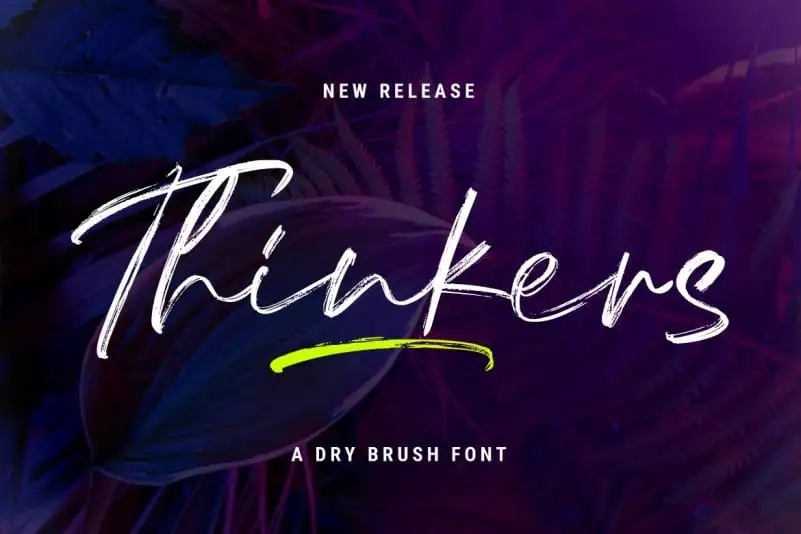
Thinkers Brush Font – Download Grátis
A Thinkers Brush Font é uma escolha ideal para quem busca um efeito fresco e natural em seus projetos digitais. Desenvolvida por FallenGraphic Studio, esta fórmula de script foi criada a partir de traçados artísticos que imitam o desenho do próprio branco de pincel, com linhas rápidas feitas pelo autor. Suas formas são suaves e fluidas, mas ainda capturam os detalhes sutis das tochas de tinta usadas em um trabalho manual. Com uma legibilidade excelente, a Thinkers Brush Font é perfeita para aplicação em design gráfico, publicidade digital e até mesmo para trabalhos de escrita formal. Seja você um designer, criador de conteúdo ou um profissional da comunicação visual, esta fonte promete deixar seu trabalho com uma aparência única e acolhedora.